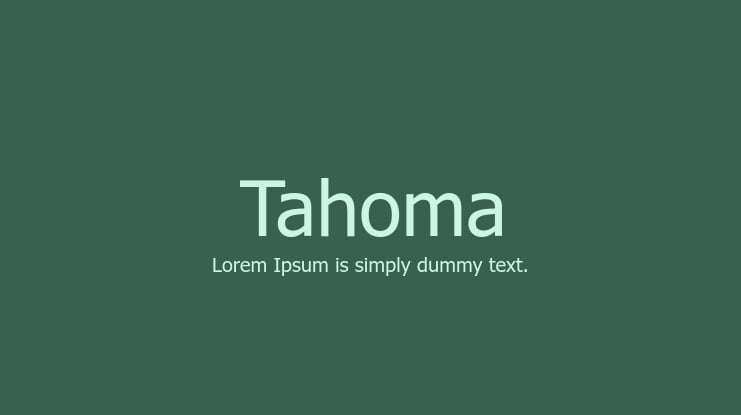
Tác giả: Matthew Carter
Ngày phát hành: 1994
Phân loại: Đơn giản
Font Tahoma là một trong những kiểu chữ phổ biến và được sử dụng rộng rãi trong thiết kế và văn bản kỹ thuật số. Font chữ này thuộc bộ font chữ không chân với đường nét rõ ràng, dễ đọc. Font Tahoma đã trở thành lựa chọn ưu tiên của nhiều nhà thiết kế và lập trình viên khi cần một font chữ đơn giản nhưng vẫn giữ được sự chuyên nghiệp. Nếu bạn đang tìm kiếm một font chữ vừa thân thiện với người dùng, vừa thể hiện sự tinh tế, thì đây chắc chắn là một sự lựa chọn không thể bỏ qua.